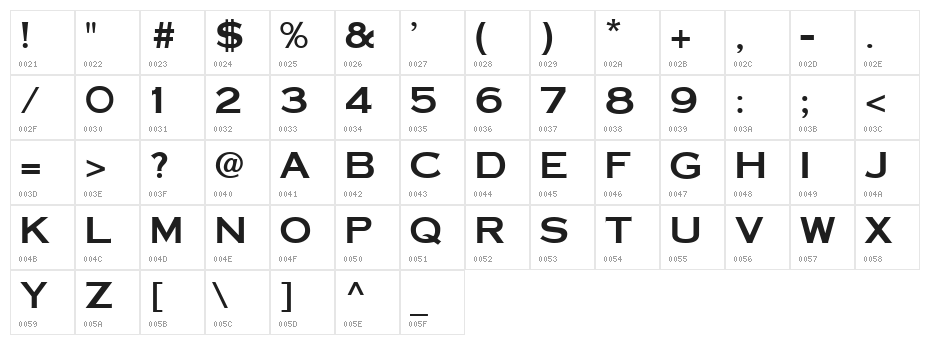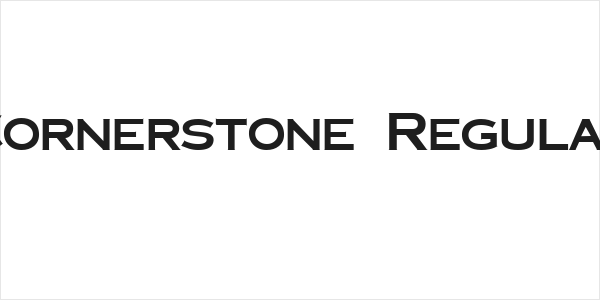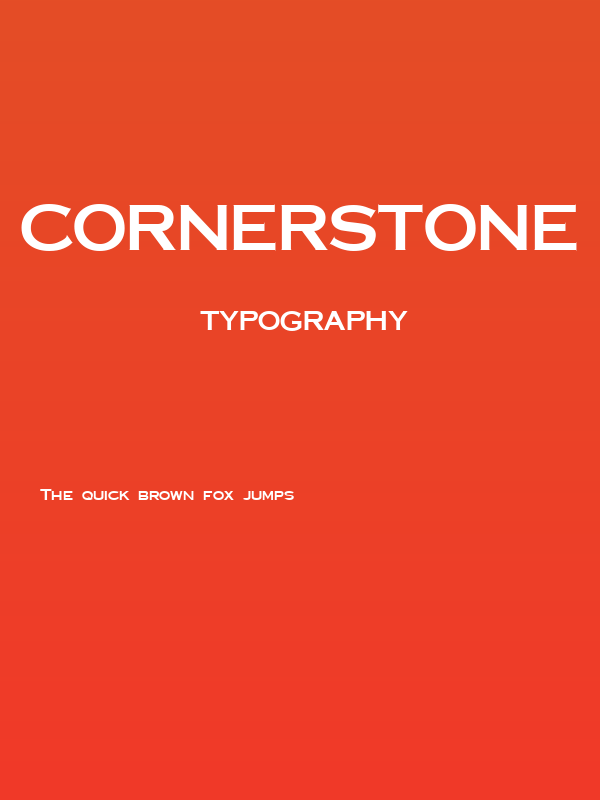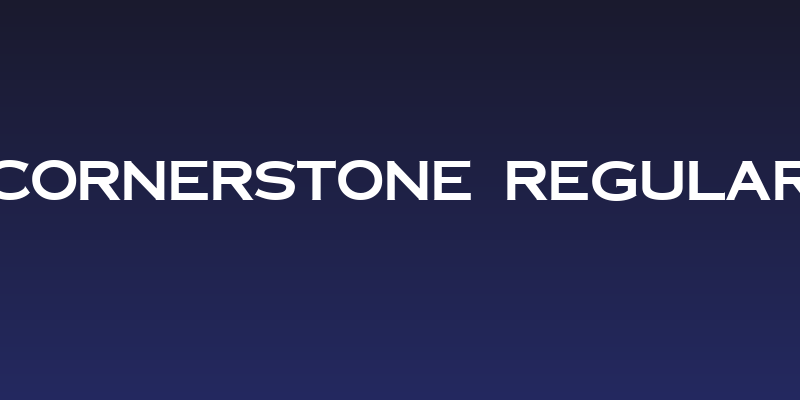
Cornerstone Regular Font
✎ Sans Serif
| Anwendungsfall | Headlines, Logos, Branding |
| Vorgeschlagene Projekte | Ideal for branding, advertising, headlines, and digital media where a modern and professional appearance is desired. |